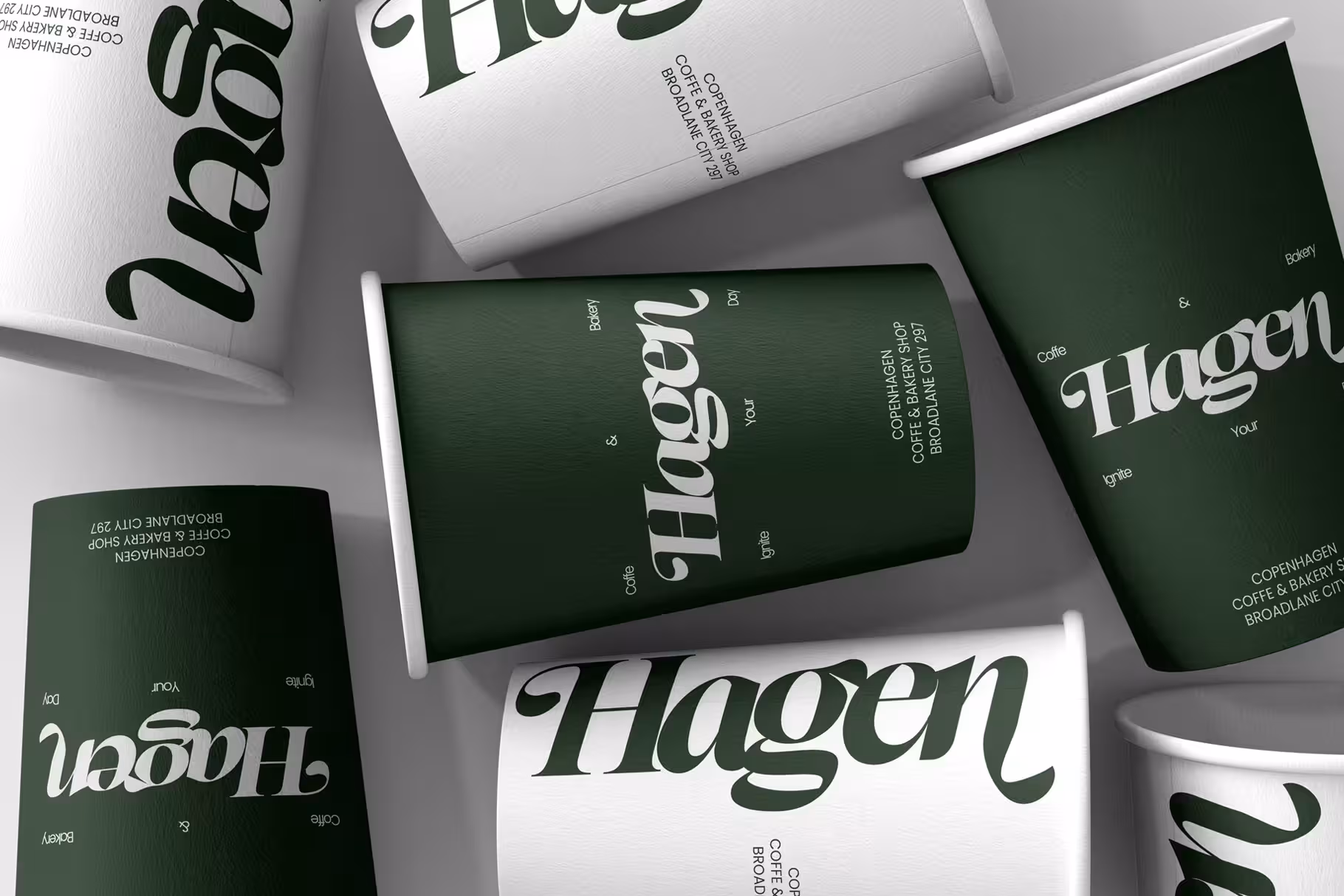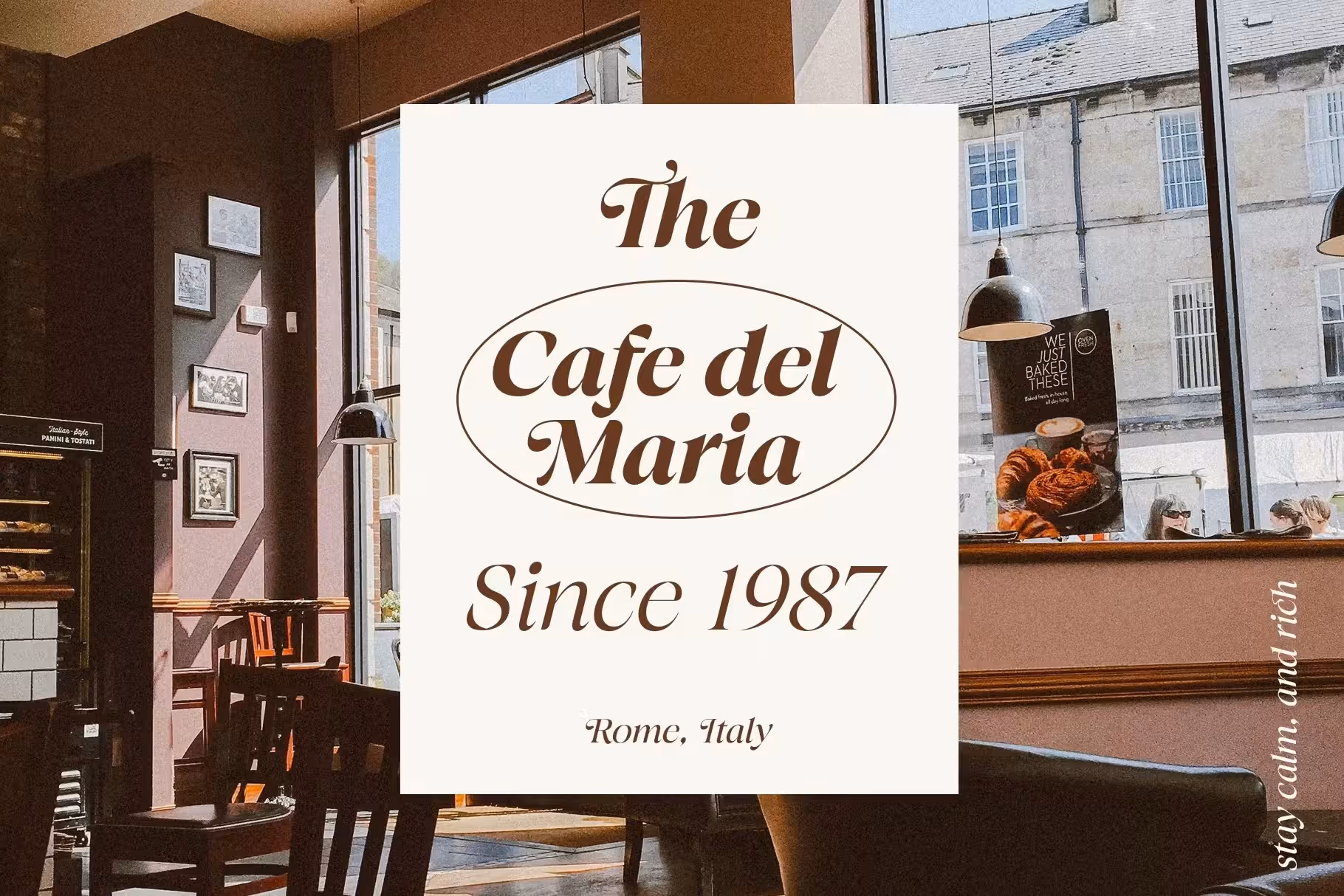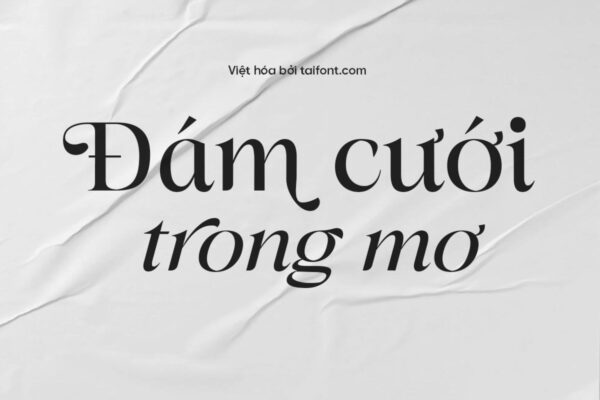
Giới thiệu về Font Taylor Belle Regular & Italic Việt hóa
Taylor Belle Việt hóa là một bộ font chữ nổi bật với thiết kế thanh mảnh, tinh tế và đầy cuốn hút. Bộ font này mang đến vẻ đẹp cổ điển kết hợp hiện đại, toát lên phong thái quý phái, đẳng cấp và sự cuốn hút đặc biệt. Với hai phiên bản Regular (thẳng) và Italic (nghiêng), bộ font này lý tưởng cho mọi ấn phẩm cần sự tinh xảo và độc đáo.
Với sự tinh xảo trong từng ký tự và tính thẩm mỹ vượt trội, Taylor Belle là lựa chọn hoàn hảo cho các thiết kế muốn truyền tải sự sang trọng và phong cách, đặc biệt là trong các lĩnh vực:
- Thiết kế tạp chí và thời trang: Hoàn hảo cho các thương hiệu thời trang cao cấp, từ logo, nhãn mác sản phẩm, đến các lookbook và chiến dịch quảng bá bộ sưu tập. Font này giúp truyền tải vẻ đẹp thanh lịch, đẳng cấp và độc đáo của trang phục, nâng tầm giá trị thương hiệu. Đặc biệt, nó lý tưởng để sử dụng cho các tiêu đề chính, lời dẫn, hoặc nội dung bài viết trong các tạp chí về thời trang, làm đẹp, lối sống cao cấp.
- Thiết kế thương hiệu quán cafe: Lý tưởng cho logo, menu hoặc bộ nhận diện thương hiệu của các quán cà phê muốn truyền tải sự tinh tế, ấm cúng và sự thanh lịch. Nét chữ có chân của font giúp xây dựng một hình ảnh thương hiệu vững chắc và dễ nhận diện.
- In ấn cao cấp: Đảm bảo khả năng đọc tốt trên giấy và tạo ấn tượng mạnh mẽ cho các ấn phẩm như brochure, catalogue, bao bì sản phẩm cao cấp, hoặc danh thiếp.
Với Taylor Belle Việt hóa, bạn có thể dễ dàng thổi hồn tinh tế, sang trọng và vẻ đẹp hoàn hảo vào các thiết kế, tạo ra những sản phẩm không chỉ đẹp mắt mà còn đầy cảm xúc và sức hút đặc biệt.